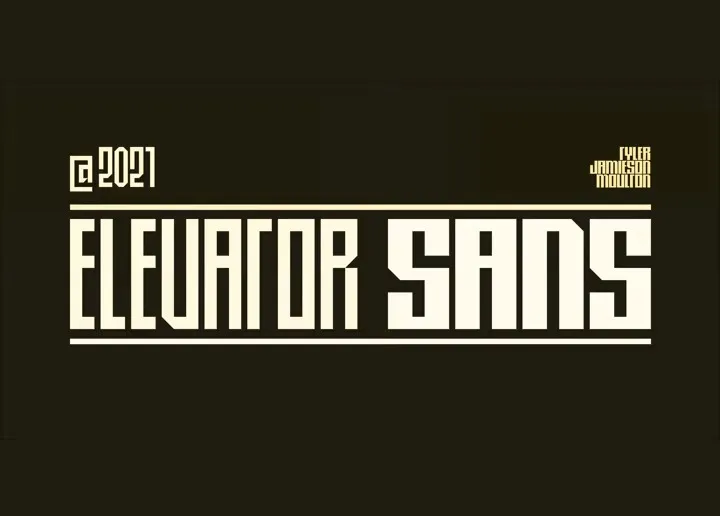
Esta é uma tipografia sans-serif em display que vem com um estilo forte. Elevador oferece uma estilização geométrica comprimida que é legível a distâncias longas e ainda mantém personalidade, elegância e substância. É perfeito para headlines, marca e design web, entre outros usos. Embora Elevador tenha sido inspirado na necessária perfeição exigida em projetos de elevadores e escadarias, seu resultado final possui uma personalidade própria. Seu estilo robusto se destaca por meio da sua tipografia curta e geométrica que é ideal para grandes espaços visuais. Este design permite um equilíbrio harmonioso entre força e elegância, tornando-o adequado tanto para ambientes profissionais quanto para aplicativos de mídia social. Elevador é perfeito para estilos modernos e minimalistas, mas ainda proporciona um toque de personalidade que o torna versátil. Seja para criar uma identidade visual forte ou para dar um ar distinto a sua próxima criação digital, Elevador tem tudo o que você precisa.